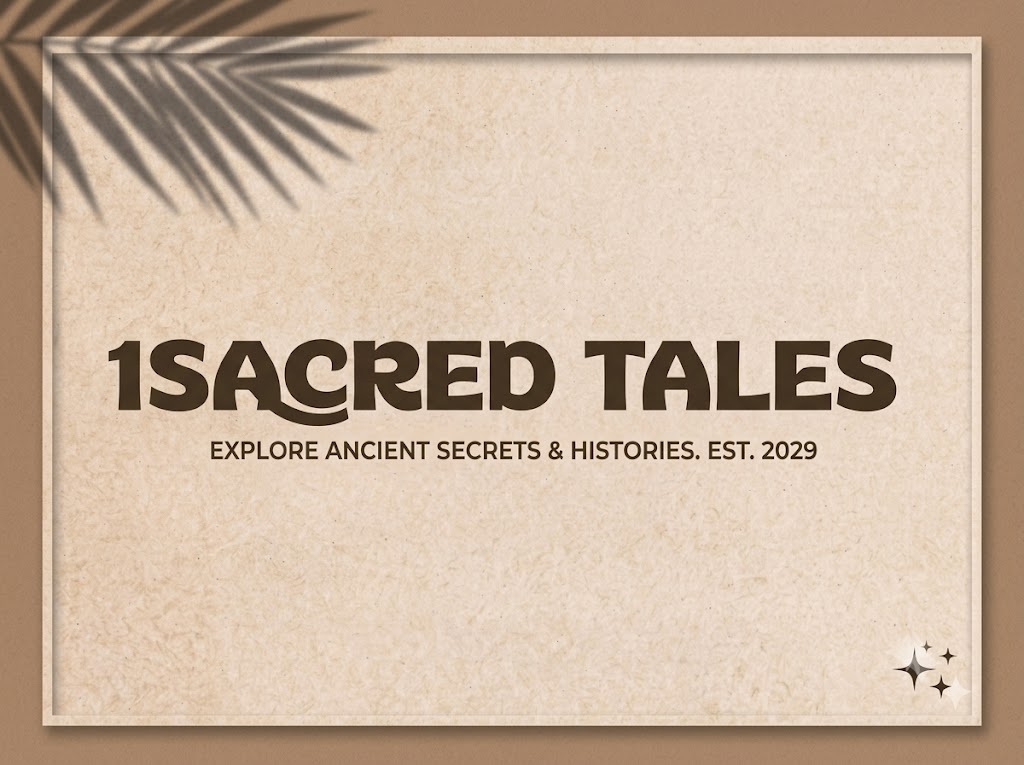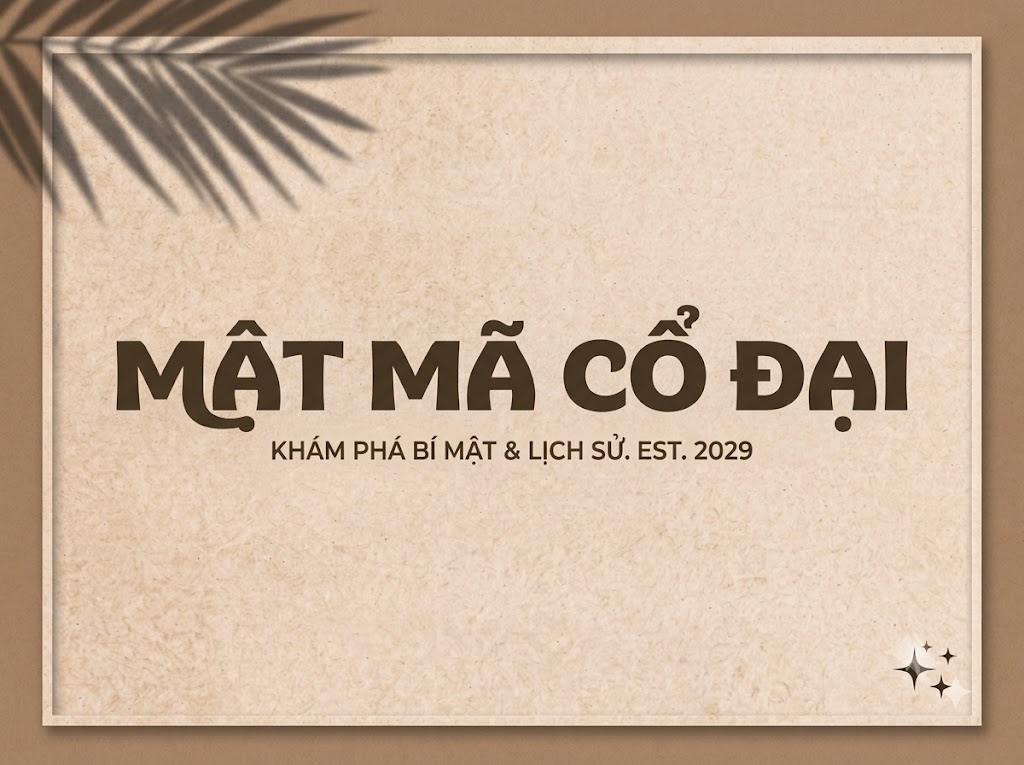
1FTV Retroguard
Trong xu hướng thiết kế đồ họa hiện đại, phong cách Retro và Vintage đang có sự quay trở lại vô cùng mạnh mẽ trên các nền tảng mạng xã hội.
Một bộ chữ tiêu đề sở hữu các đường nét biến tấu ngẫu hứng, mang đậm âm hưởng cổ điển sẽ giúp ấn phẩm truyền thông của bạn tự động kể một câu chuyện đầy cá tính.
Nếu bạn đang tìm kiếm một phông chữ hiển thị dày dặn, mang tinh thần hoài cổ phóng khoáng để làm bừng sáng các thiết kế banner hay video ngắn, thì font 1FTV Retroguard chính là sự lựa chọn không thể bỏ qua.
Giới thiệu về font 1FTV Retroguard
Font 1FTV Retroguard là một bộ chữ hiển thị không chân (sans-serif) sở hữu phong cách thiết kế mang đậm dấu ấn của thập niên 70 – 80, pha chút hơi hướng phá cách nghệ thuật.
Nhờ cấu trúc kỹ thuật đồng bộ này, phông chữ mang đến khả năng hiển thị vô cùng sắc nét, giúp bạn tự tin ứng dụng trên mọi phần mềm thiết kế và dựng phim chuyên nghiệp mà không lo gặp lỗi vỡ nét hay răng cưa khi phóng lớn.
Đặc điểm nổi bật của phong cách thiết kế Retroguard
Sức hút lớn nhất của font 1FTV Retroguard đến từ cấu trúc chữ khối dày dặn (heavy bold) kết hợp cùng những đường uốn lượn biến điệu vô cùng độc đáo bên trong từng ký tự.
Phông chữ được xây dựng theo định dạng All-Caps (thiết kế viết hoa đồng bộ cho toàn bộ hệ thống), mang lại sự cân bằng tuyệt đối về mặt cao độ và tạo ra các khối chữ vô cùng vững chãi, bắt mắt.
Điểm nhấn nghệ thuật đắt giá nằm ở cách tạo hình đầy ngẫu hứng trên các ký tự như chữ B, R, O, G. Đội ngũ thiết kế đã khéo léo kéo dài phần chân chữ thành các đường uốn swash điệu nghệ, hoặc lồng ghép các nét lượn sóng mềm mại ngay giữa thân chữ.
Sự kết hợp tài tình giữa phom chữ đứng cứng cáp và nét uốn mượt mà tạo nên một diện mạo vừa hoài cổ, vui nhộn, lại vừa mang tinh thần tự do, nổi loạn đầy tính nghệ thuật.
Hệ thống khoảng cách chữ (kerning) và độ giãn dòng đã được căn chỉnh chuẩn xác, giúp các ký tự độc lạ khi đứng cạnh nhau luôn giữ được sự liền mạch mà không bị dính nét hay gây cảm giác rối mắt cho người xem.
Bên cạnh hệ thống chữ cái viết hoa đồng bộ, phông chữ còn tích hợp đầy đủ dãy số từ 0-9 cùng hệ thống các ký tự đặc biệt, dấu câu thông dụng (1234567890.:,;'"(!?)+-*/=).
Bản Việt hóa chuẩn chỉnh này giúp các nhà sáng tạo nội dung hoàn toàn yên tâm thiết kế các văn bản tiếng Việt có dấu mà không lo gặp phải tình trạng lỗi hiển thị hay nhảy font khó chịu.
Hình ảnh demo thực tế của font 1FTV Retroguard
Để giúp bạn dễ dàng hình dung khả năng co giãn và hiển thị linh hoạt của phông chữ này trên các kích thước khác nhau, hãy cùng xem qua bảng mô phỏng thực tế từ file hệ thống image_c85f81.png:
Kích thước nhỏ (12pt – 24pt): Dù sở hữu nhiều đường uốn lượn biến điệu phức tạp và nét chữ dày, các khối chữ vẫn hiển thị rõ ràng, ngay ngắn và dễ đọc trên giao diện màn hình di động cỡ nhỏ.
Kích thước lớn (36pt – 72pt): Đây là đất diễn lý tưởng nhất để font chữ phô diễn toàn bộ sự bay bổng, hầm hố, tạo hiệu ứng thị giác hoài cổ vô cùng mạnh mẽ cho các dòng headline chính.
Ứng dụng của font Retroguard trong thiết kế đồ họa và làm video
Sở hữu nét cá tính độc lạ, hoài cổ và cấu trúc hình khối đậm nét, font 1FTV Retroguard mở ra không gian sáng tạo vô cùng rộng lớn cho các dự án truyền thông hiện đại:
Làm tiêu đề video ngắn (TikTok, Reels, Shorts): Khối chữ siêu đậm, rõ ràng và cực kỳ bắt mắt giúp các câu giật tít, từ khóa chính thu hút người xem lướt feed dừng lại ngay lập tức. Phông chữ này hiển thị đặc biệt ấn tượng trên các khung hình đứng 9:16 của thiết bị di động.
Thiết kế ảnh thu nhỏ YouTube (Thumbnail): Đây là vũ khí hạng nặng để tăng tỷ lệ nhấp chuột cho các video thuộc chủ đề vlog đời sống, review ẩm thực, phong cách sống retro, hoặc các nội dung giải trí, âm nhạc lofi, acoustic nhờ độ dễ đọc từ khoảng cách xa.
Banner và Poster quảng cáo sự kiện nghệ thuật: Cực kỳ hoàn hảo cho các poster phim indie, banner chương trình âm nhạc cổ điển, hội chợ vintage hoặc các chiến dịch marketing cần sự hoài niệm, phá cách.
Nhận diện thương hiệu phong cách hoài cổ: Phù hợp làm logo dạng chữ khối, biểu ngữ quảng cáo hoặc thiết kế nhãn mác, bao bì sản phẩm cho các tiệm cà phê, thương hiệu thời trang local brand hướng tới sự bụi bặm, cá tính.